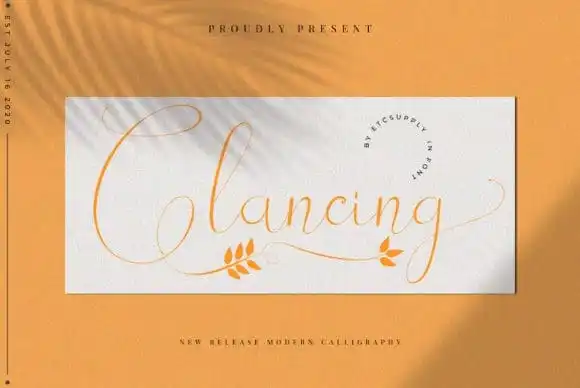
Glancing Calligraphy Font – Fonte Grátis
Glancing Calligraphy Font
A Glancing Calligraphy Font é uma nova tipografia de script calligrafia projetada para aprimorar suas próximas ideias criativas. Ideal para aplicação em watermark na fotografia, citações, capas de álbum, logotipos e cartões de visita, entre outros projetos de design. Essa fonte moderna é baseada em calligrafia inspirada por artistas existentes, com seu estilo balançante. É perfeitamente adequada para design relacionado a moda ou tendência. A fonte Glancing Calligraphy foi criada pelo designer Etc-Supply, uma escolha ideal para quem busca um novo elemento de personalização em seus projetos gráficos.